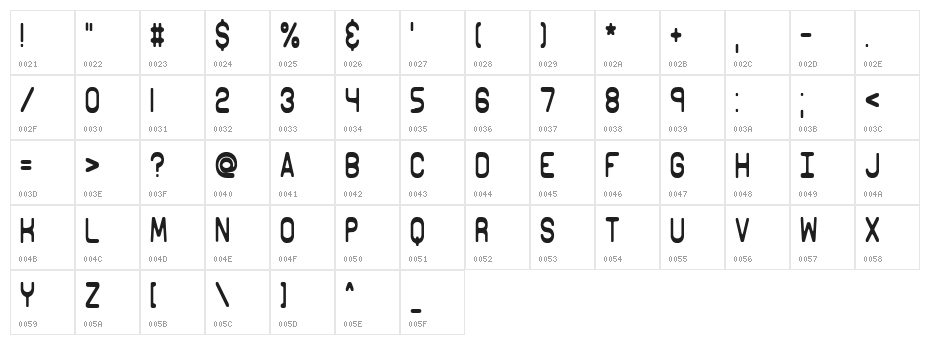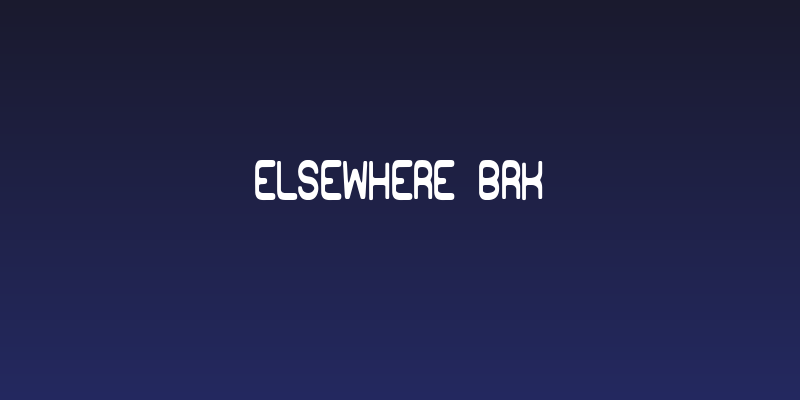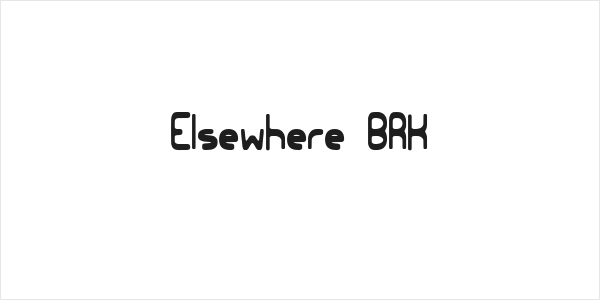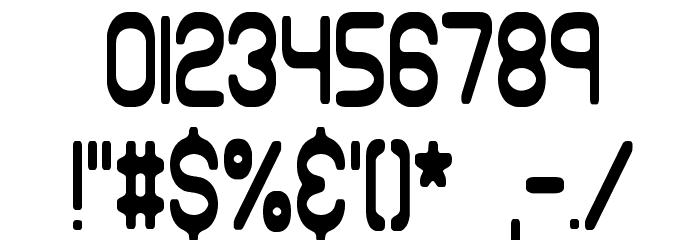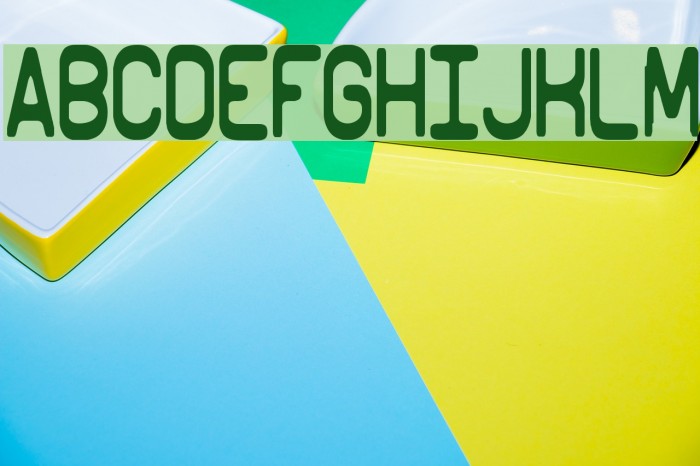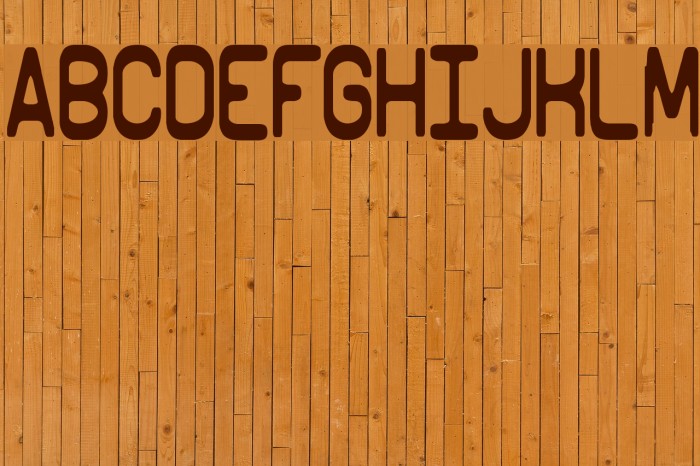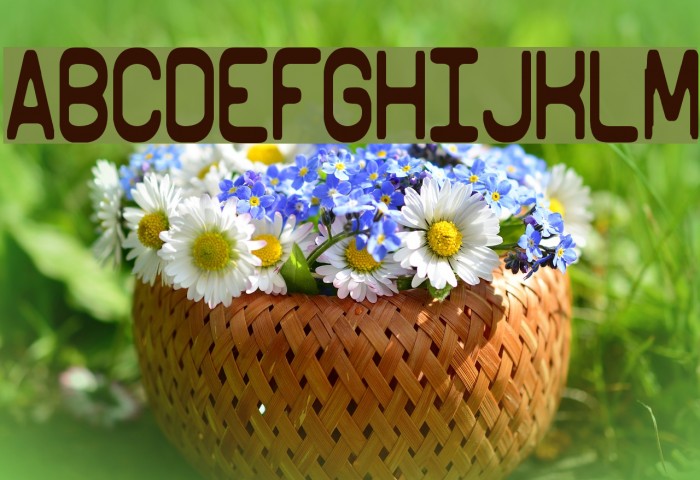
Elsewhere BRK Font
✎ Quirky
| Proiecte propuse | Ideal for children's books, playful branding, posters, and creative projects that require a friendly and approachable typeface. |